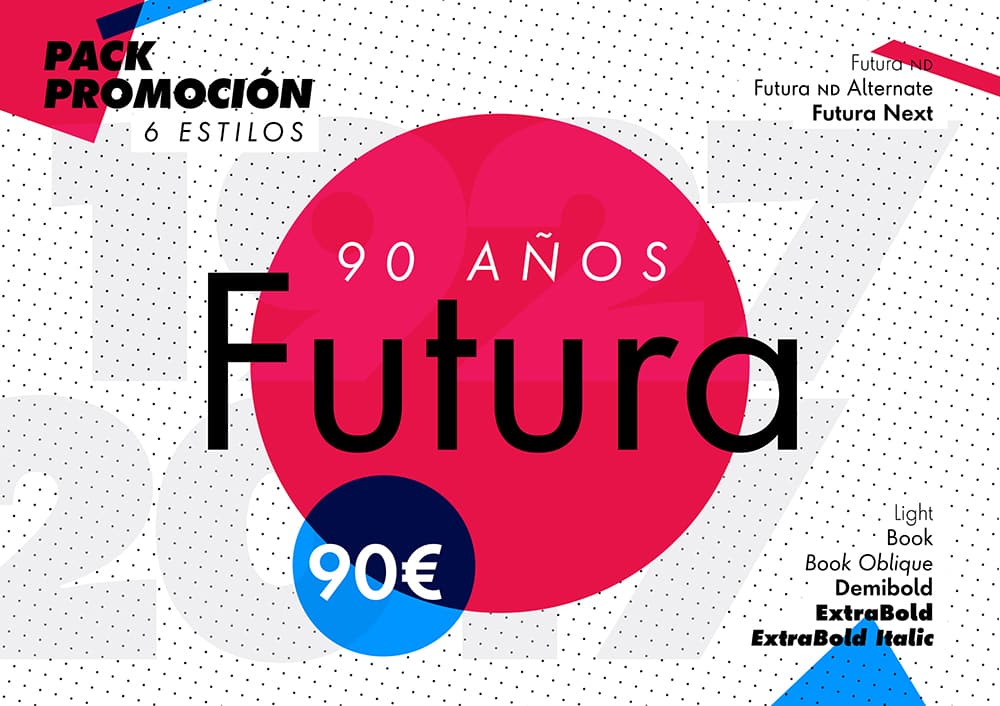
Futura nace en el seno de una familia de espíritu moderno e innovador, la Fundición Bauer. Su padre, Paul Renner, lo tenía claro: crear un tipo del hoy y del mañana.
Así aparece en sociedad bajo el lema La escritura de nuestro tiempo. Era allá por 1927 y, desde entonces, no ha dejado de serlo ni un sólo día.
La inmediatez de su éxito hizo que se convirtiera en la estrella de múltiples cubiertas de libros e impresos, pero la fama nunca le afectó. Se ha mantenido impasible ante el paso del tiempo, siempre fuerte, elegante y, aunque hoy cumpla 90 años, sigue siendo joven. Eternamente joven.
De apariencia limpia y clara, sentó las bases de la Nueva Tipografía. Siempre fiel defensora del Movimiento Moderno sobrevivió a la II Guerra Mundial y al nazismo, a pesar de que provocó el destierro de su creador.
Viajó y viajó, haciéndose popular en todos los rincones del planeta e incluso en el espacio. Siendo la tipografía corporativa de la Misión del Apolo 11 y llegando a pisar la luna.
Fue la aliada de Barbara Kruger a la hora de fortalecer los mensajes feministas y sarcásticos de su obra.
Ha sido la diva de Stanley Kubrick, siendo la protagonista de las carteleras de su filmografía.
Era la tipografía preferida de Stanley. Es una sans-serif. Le gustaba también Helvetica y Univers por su elegancia y limpieza… Siempre traté de persuadirlo de olvidarla. Pero en cuanto la conoció, se casó con ella.
ANTHONY FREWIN
(asistente personal de Stanley Kubrik)
Para Wes Anderson también ha sido un personaje clave en sus películas.
Futura tuvo tanto éxito en los años 90 que un puñado de directores de arte, aburridos de su popularidad, lanzaron una contracampaña para boicotear su uso.
Pero claro, este movimiento fracasó, ya que Futura se había hecho un gran hueco en la escena y contaba con multitud de fans incondicionales.
Fue y es la madre y precursora de las tipografías geométricas. Con su aparición por fin hizo funcionar las formas geométricas preferidas por las corrientes modernistas que, sin embargo, no acababan de funcionar en las letras propuestas por sus representantes, como por ejemplo la Bauhaus. Futura sustituyó la geometría matemática por la que percibe nuestro ojo, logrando poner en valor todo el atractivo inherente a la simpleza geométrica a través de un sinfín de correcciones ópticas.
Ha salido ilesa a la evolución tecnológica. Ha vestido el plomo pero no la costó nada lucir, con elegancia y desparpajo, el píxel.
Desde hace décadas hasta el día de hoy ha sido la tipografía encargada de lanzar los mensajes, directos y contundentes, para Nike. Llegando a crear su propia versión de tipografía corporativa: Futura ND for Nike 365 Condensed Extrabold.
Futura está omnipresente, viste en todo tipo de aplicaciones y es apreciada en todo tipo de soportes. Muchas y renombradas marcas son las que han confiado en ella para consolidar su imagen.
Su vida ha sido apasionante y su carácter nunca ha dejado de ser joven, ¡y lo que le queda! Porque siempre aporta un plus de elegancia, de fortaleza y de seriedad. Un tipografía con una gran personalidad, que ha demostrado ser universal: la tipografía de todos los tiempos.